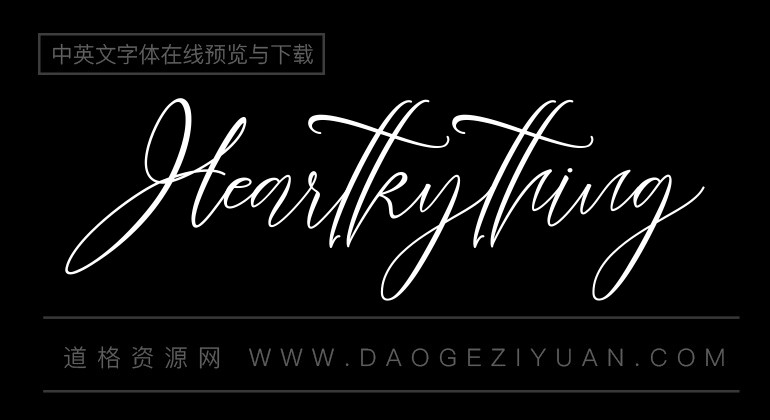
Heartkything
Heartkything是一款简洁优雅的英文字体,它的字体风格灵感来源于年轻的爱情,它的字体风格有着柔和的曲线,温柔的笔触,圆润的结构,给人一种温馨的感觉。它的字体特点是简洁优雅,适合用于设计海报、标识、名片、婚礼邀请函等。
Heartkything是一款非常不错的手写艺术字体,具有很好的视觉感,适合于文化类的宣传设计、商业类品牌的广告和产品包装设计以及个性化文字排版等较多场景。
Heartkything字符映射图